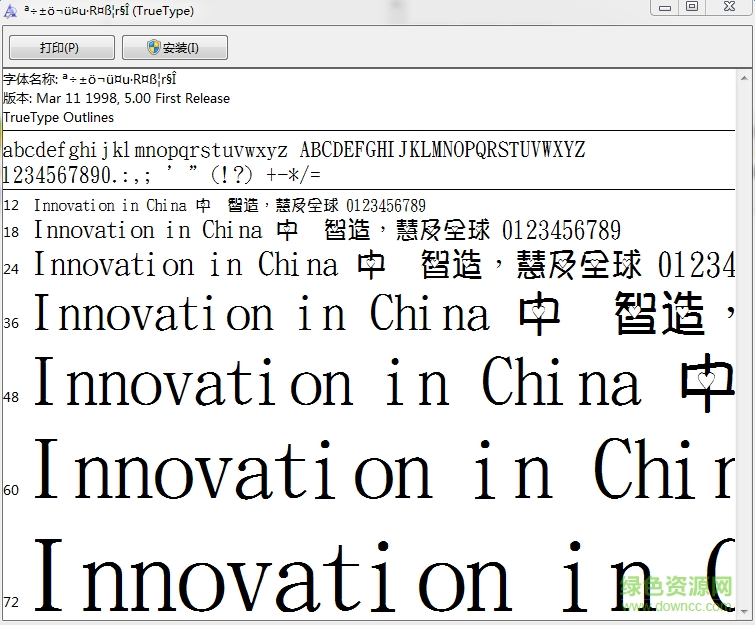
金梅美工愛心字形是金梅字體的一種繁體字體,雖是繁體字,但是沒有那么的復雜,也比較好認,也算是中國字體中的一種比較特殊的字體,應用范圍也挺廣的,有需要的朋友可以來綠色資源網下載。
浪漫漫個性的中文字體,不過這款字體是繁體版本,字體的中間都有一個愛心,看起來浪漫極了,可以應用于各類宣傳海報、影視設計或者PPT設計等領域,有喜歡這款字體的朋友快快下載吧。